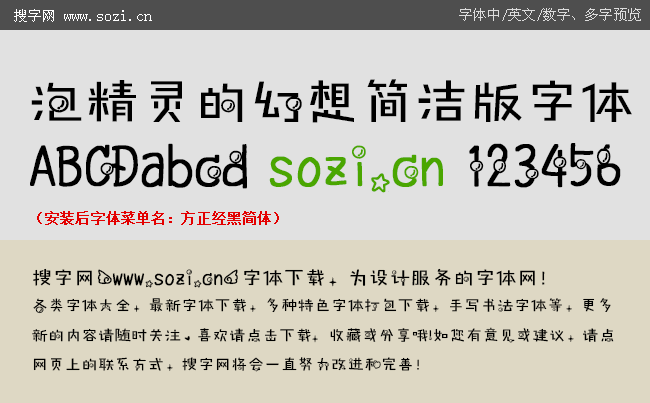
泡精靈的幻想簡潔版字體
搜字網(wǎng)給大家提供一款泡精靈的幻想簡潔版字體手機(jī)中文字體下載。這款手機(jī)字體是以方正經(jīng)黑體為原形,字體和標(biāo)點(diǎn)被裝飾了卡通泡泡圖案,經(jīng)黑字體字形清秀,大方美觀,加入圖案裝飾后卡通味特別濃,特別適合喜歡手機(jī)字體個(gè)性一些的朋友在手機(jī)上安裝使用。